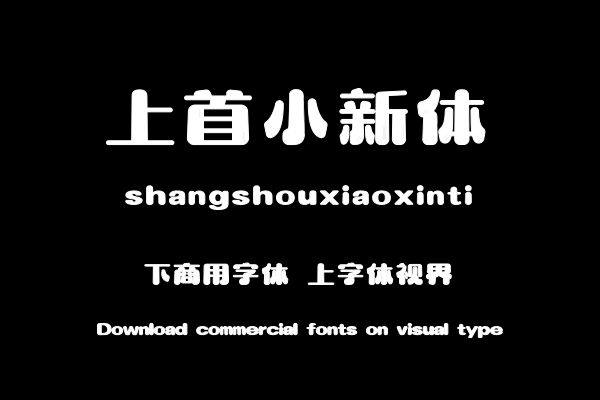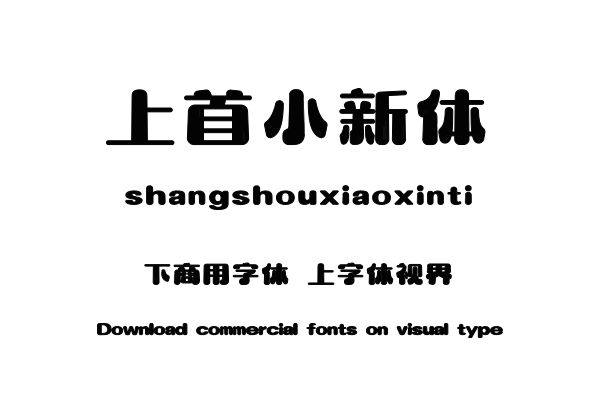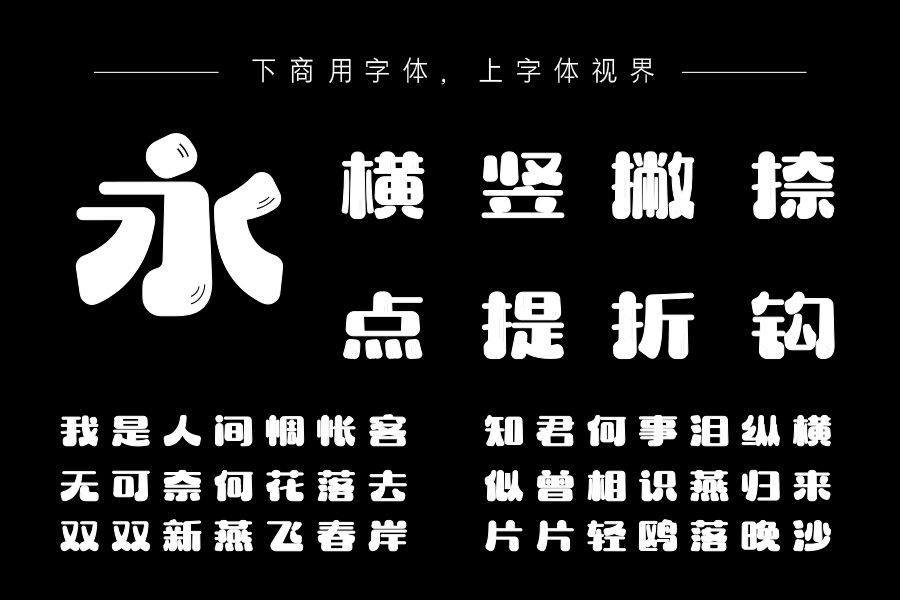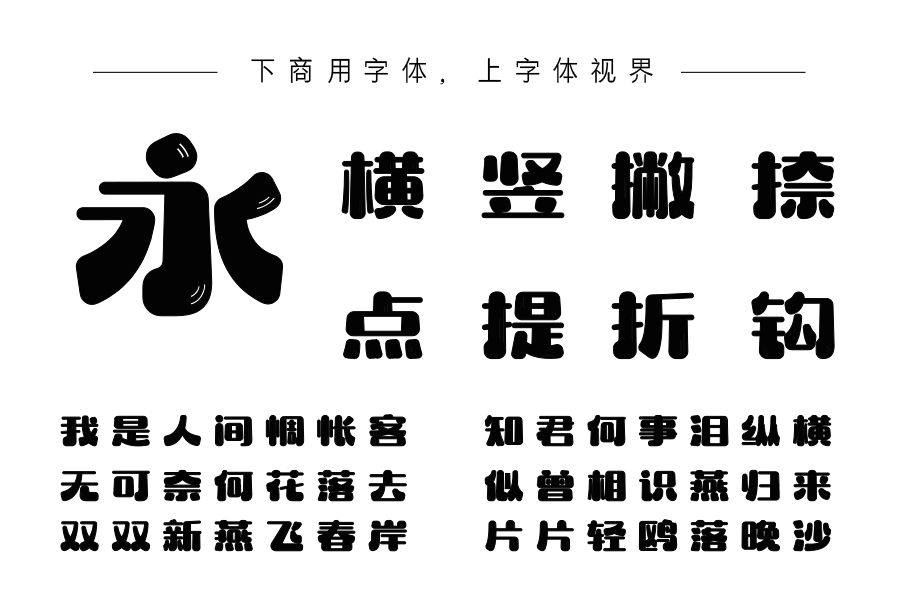
字体笔画采用横细竖粗的方式让笔画中通入独特的弧度和竖线形成一种跳跃的画面感,圆圆的线条让字体更加Q弹活泼,使整体风格鲜活大胆有趣。购买须知:“下载服务费”与“字体VIP”所获得字体 仅用于个人非商用, 商用请联系付费授权。本字体为电脑用字,手机没有root权限不支持直接手机换字(手机如何root,请自行百度搜索教程)。购买前请先 了解清楚后再付款 ,字体为虚拟产品无法回收 一旦购买不支持退款。